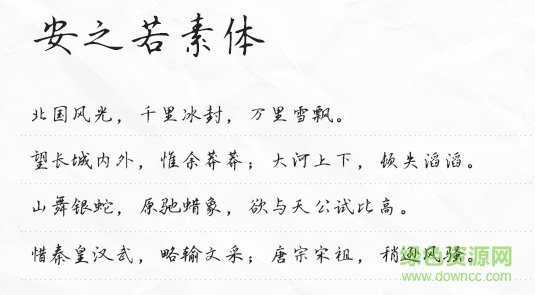
安之若素體是思雨字體推出的硬筆手寫體,很有楷書字體和隸書書法字體的運(yùn)維,給人干凈簡(jiǎn)潔的娟秀之美,讓文字更有質(zhì)感和藝術(shù)效果,使用范圍較廣,快來綠色資源網(wǎng)搶先體驗(yàn)吧!
“繁華盡處,尋一處無人山谷,建一木制小屋,鋪一青石小路,與你晨鐘暮鼓,安之若素?!薄仓羲伢w。
本字體是在國家標(biāo)準(zhǔn)簡(jiǎn)體字庫GB2312所包含6763漢字的基礎(chǔ)上,又增加了近200常用字,已經(jīng)覆蓋了大陸99.75%的漢字使用頻率,足以滿足日常需求。
安之若素體給人寧靜現(xiàn)世時(shí)光安好的淡泊感慨,清新有力的筆觸讓自己免于拖泥帶水的雜亂,秀氣端莊的外觀更顯兼具時(shí)尚和復(fù)古之味,給你的平面設(shè)計(jì)更添美感!